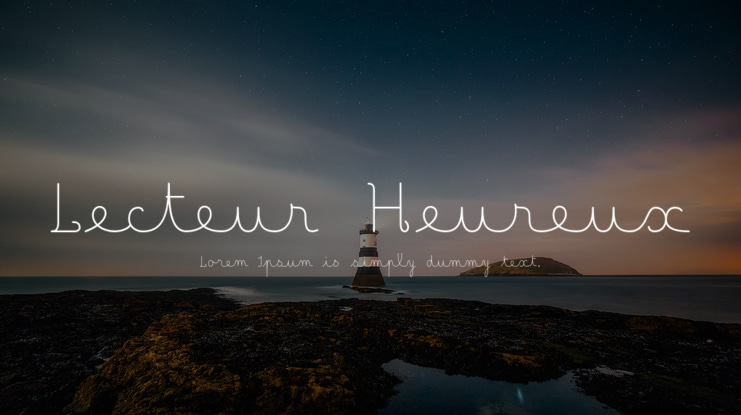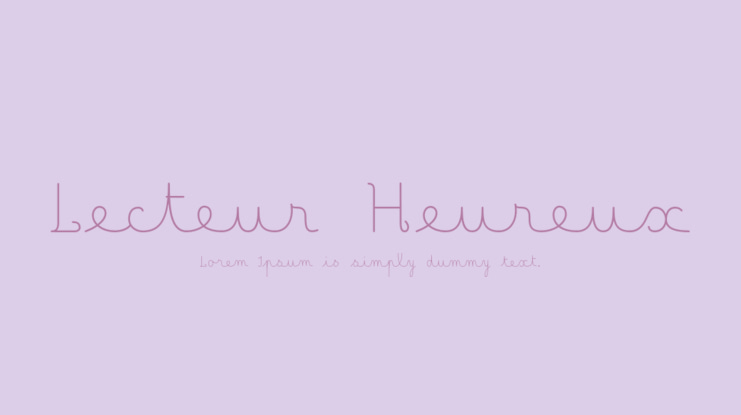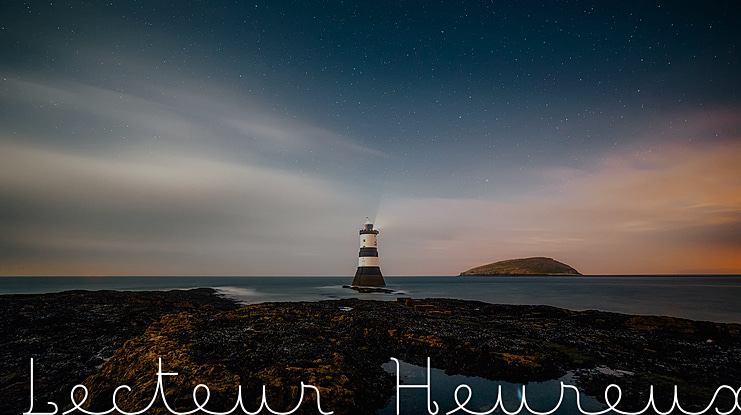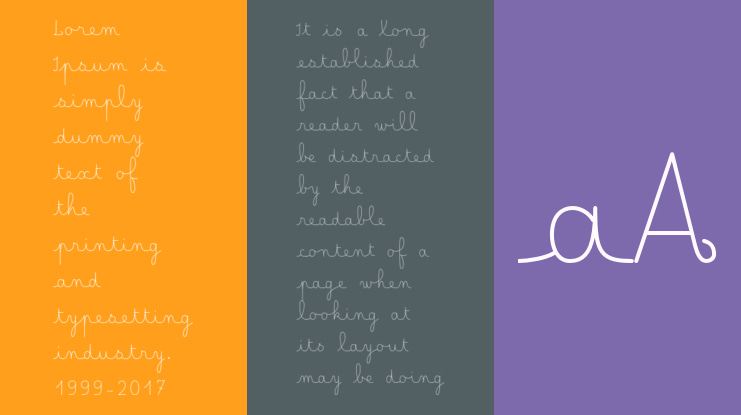
Lecteur Heureux Font
La lecture des enfants dyslexiques est facilitée si les lettres sont espacées. Lecteur Heureux est conçue pour eux. Cette fonte nécessite absolument que votre traitement de texte utilise les Alternatives contextuelles.
Reading is easier for dislexic children if letters are spaced out. Lecteur Heureux is conceived for them. This font requires absolutely that your word processor uses Contextual Alternates.